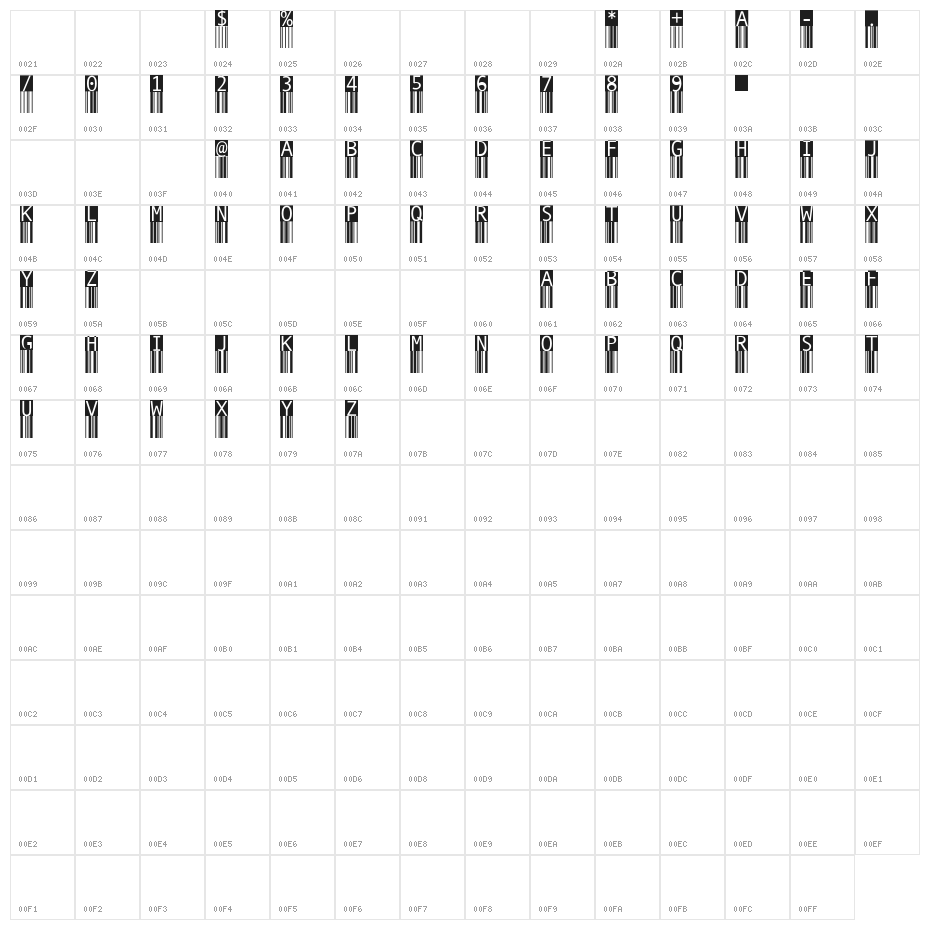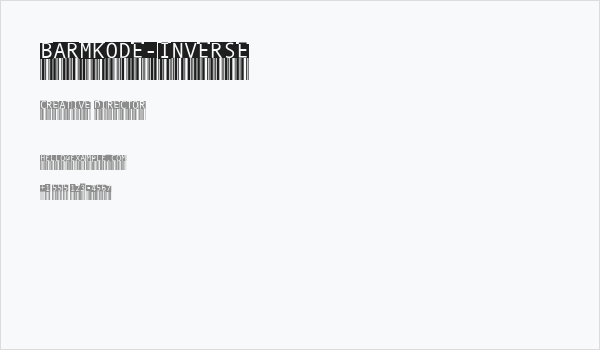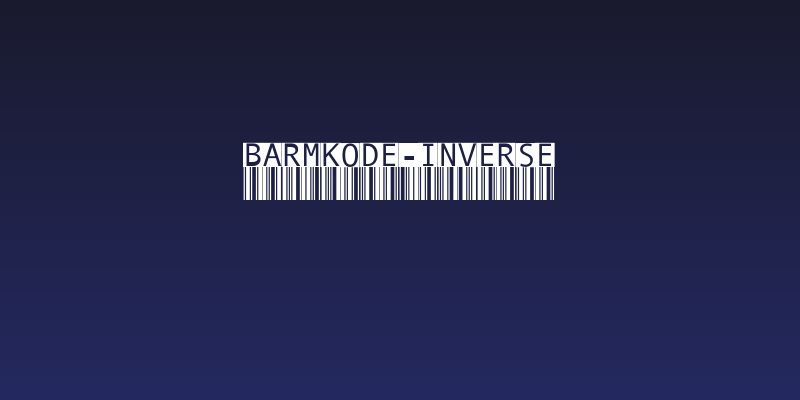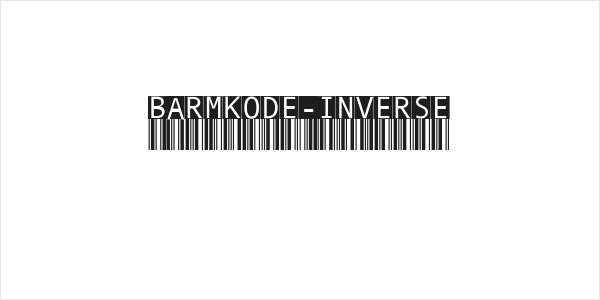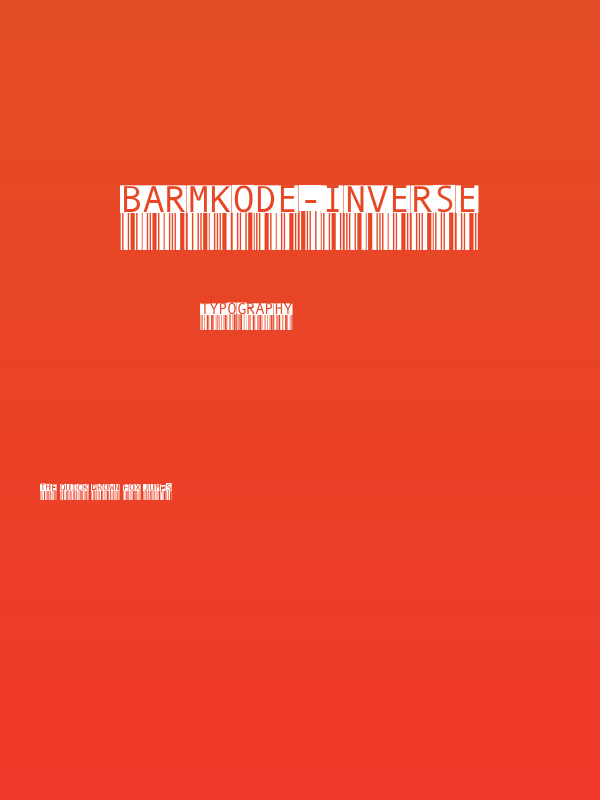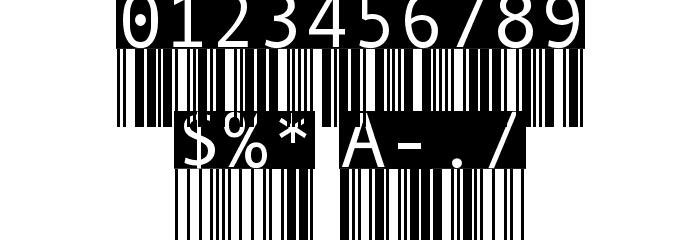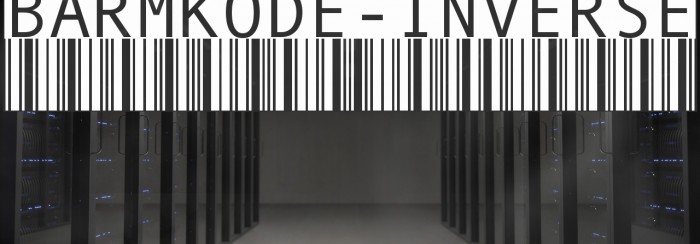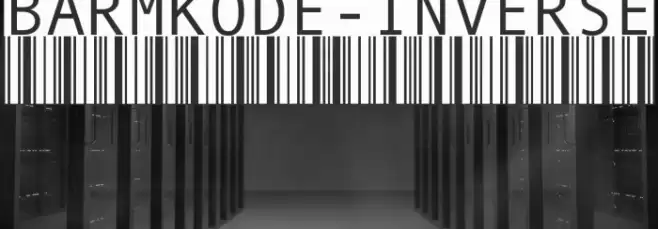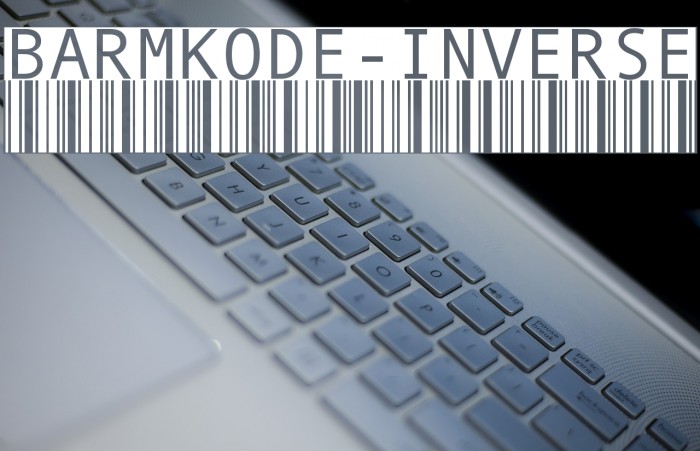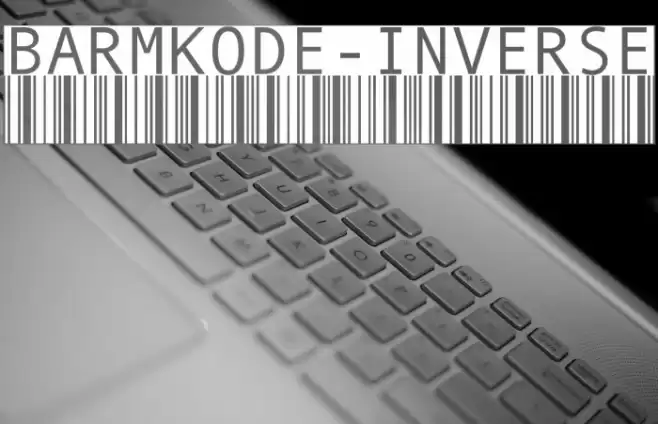
BarMKode-Inverse Font
| Anwendungsfall | Logos, Posters, Branding |
| Vorgeschlagene Projekte | Ideal for branding, packaging, tech-themed events, futuristic posters, and any project requiring a modern, innovative look. |